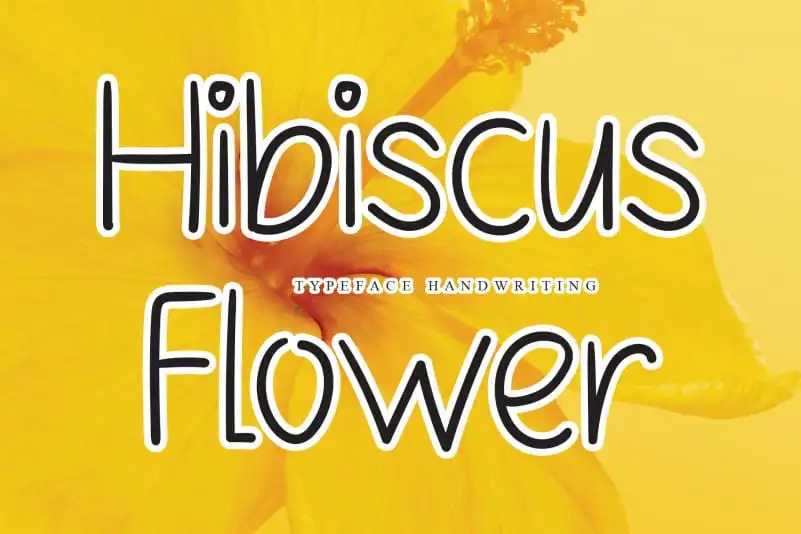
Hibiscus Flower Handwritten Font – Download Grátis
A fonte ‘Hibiscus Flower Handwritten Font’ é uma escolha perfeita para quem busca um visual simples e natural no design. Esse fonte se destaca pela sua composição natural, com letras largas e espaçadas, o que a torna ideal para destacar cada projeto. Com seu aspecto suave e fluido, esta fonte é uma ótima opção para designers de gráficos digitais querendo criar designs distintos e agradáveis aos olhos do público. Ideal tanto para uso pessoal quanto profissional, ela se adapta perfeitamente às diversas necessidades do design, desde cartões de apresentação até postagens no Instagram. A fonte ‘Hibiscus Flower Handwritten Font’ é um complemento indispensável para designers que valorizam a exata harmonia entre a elegância e a naturalidade. Seu estilo único permite criar designs autênticos e singulares, sem perder sua essência simples e aconchegante. Este fonte foi criado pelo designer andikastudio, conhecido por suas criações de alta qualidade que atendem às necessidades específicas dos designers, como essa fonte elegante e versátil.